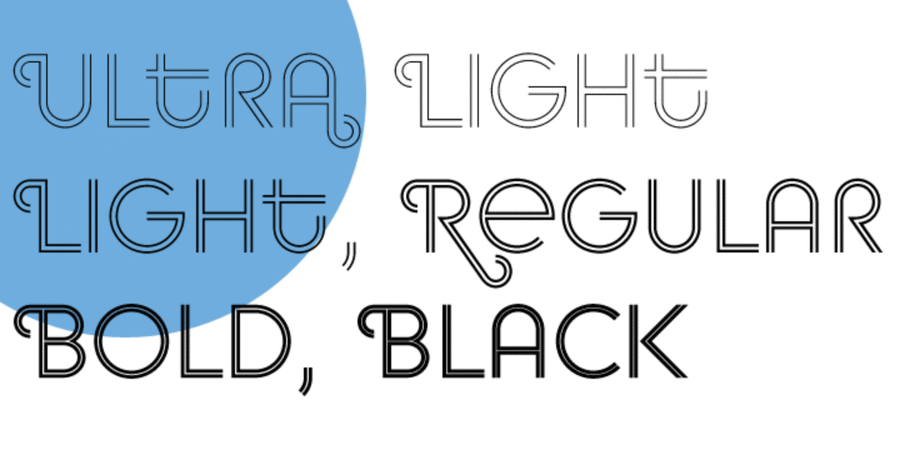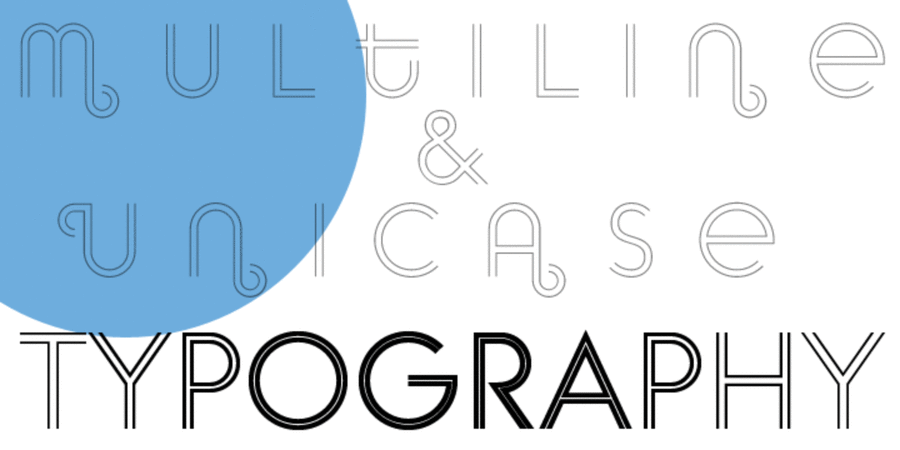
Кайли – трендовый декоративный шрифт для заголовков и плакатов. Разработан в 2011 году Сергеем Ткаченко.
Особливості сімейства шрифтів Kylie 4FХіт десятиліття:
Асоціації з сімейством шрифтів Kylie 4FОсобистість і характер гарнітури:
делікатний, чистий, легкий, модний, тонкий, оригінальний, виразний, лаконічний, якісний, молодіжний, дзвінкий, позитивний, артистичний, сучасний, міський, святковий, музичний, популярний, скляний, прозорий, точний, свіжий, дорогий, ніжний, повітряний, невагомий, танцювальний, худий, клубний, нічний
парфумерія, лосьйон, краса, туалетна вода, прикраса, косметика, мода, інтер'єр, розваги, аксесуари, театр, одяг, музика, перукарня, дизайн, дискотека, танці, аквадискотека, шампунь, відпочинок, коктейль, бар, кафе, пляж, телебачення, шоу, мюзикл, естрада, нічний клуб, вечірка, тусовка, танець, рок-н-рол, взуття Гарнітура має ознаки стилів: